한글날을 기념하여 다양한 기업, 단체에서 무료 폰트를 만들어 배포했다. 기업전용서체부터 사회공헌의 일환으로 제작된 폰트까지 각각 고유한 의미가 담겨 있다. 개성 넘치는 다섯 가지 무료 폰트를 만나보자.
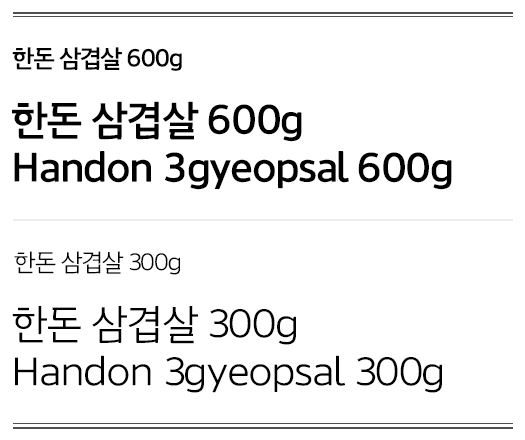
1.한돈 삼겹살체
한돈자조금관리위원회는 한돈데이(10.01)와 한글날을 기념하여 ‘한돈 삼겹살체’를 산돌커뮤니케이션과 공동 제작했다. 한돈의 친근하고 인간적인 이미지를 폰트에 녹여내기 위해 손글씨 형태로 기획되었다. 특히 자음 ‘ㄹ’은 마치 삼겹살을 겹겹이 올려놓은 것 같은 모양을 연상시켜 쓰는 즐거움도 제공한다.
한돈 삼겹살체는 Bold, Light 두 가지 웨이트로 구성되어 있고, 웨이트를 삼겹살 무게 600g과 300g으로 표현한 재치있는 작명도 눈길을 끈다. 한돈 삼겹살체는 한돈 홈페이지에서 회원가입 후 내려받아 사용할 수 있으며, 상업적인 행위는 금지되어 있다.
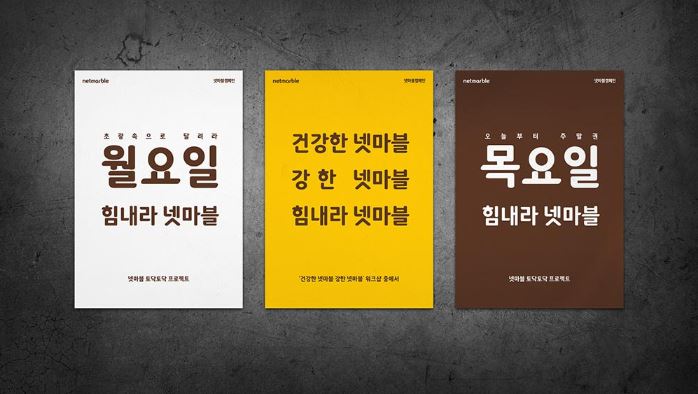
2. 넷마블체
넷마블은 기업의 정체성을 좀 더 친근하게 전달하고자 ‘넷마블체’를 제작했다. 이 폰트는 넷마블 마스코트 공룡 캐릭터인 ‘ㅋㅋ’의 실루엣을 형상화한 서체로 가독성을 고려해 만들어졌으며, 인쇄물이나 모니터에서 모두 잘 읽히는 것이 장점이다.
쭉 뻗은 직선이 매력적인 넷마블체는 Bold, Medium, Light 3종으로 구성돼 있다. 넷마블은 앞으로도 게임아카데미, 게임소통교육교재 등에 폰트를 적극적으로 활용할 예정이다.
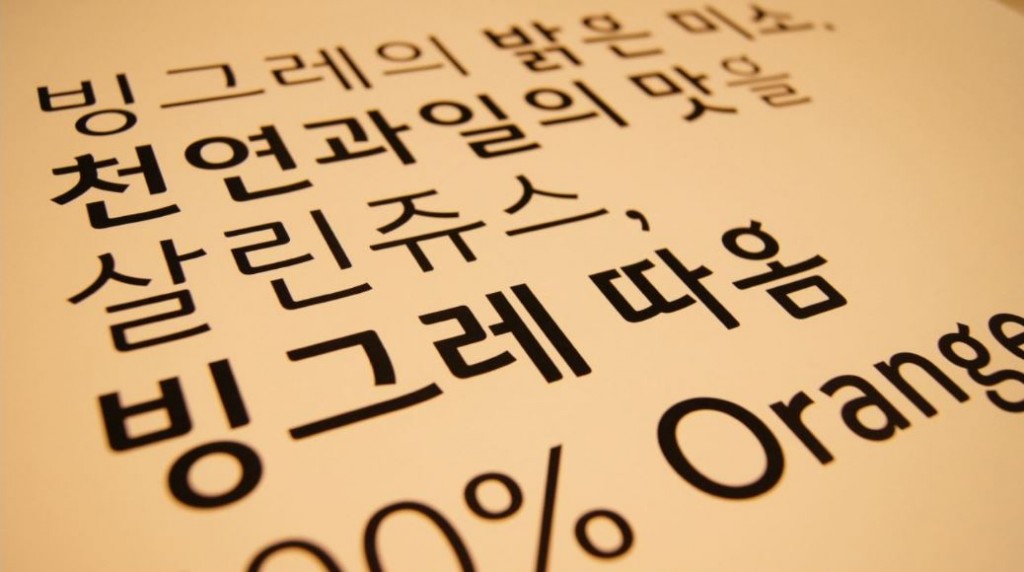
3. 빙그레 따옴체
바나나맛 우유 로고를 서체로 제작해 인기를 끌었던 빙그레는 한글 서체 시리즈 세 번째로 ‘빙그레 따옴체’를 출시했다. 과일쥬스 ’따옴’의 로고 디자인을 소재로 빙그레와 윤디자인그룹이 공동 제작하였다. 자음 이응에 쓰이는 나뭇가지 형상이 독특한 특징이다.
빙그레 따옴체는 한글날을 기념하여 훈민정음 서문의 옛한글 31자도 추가 됐으며, 세종대왕기념사업회와 한국글꼴개발연구원에 자문을 받았다.
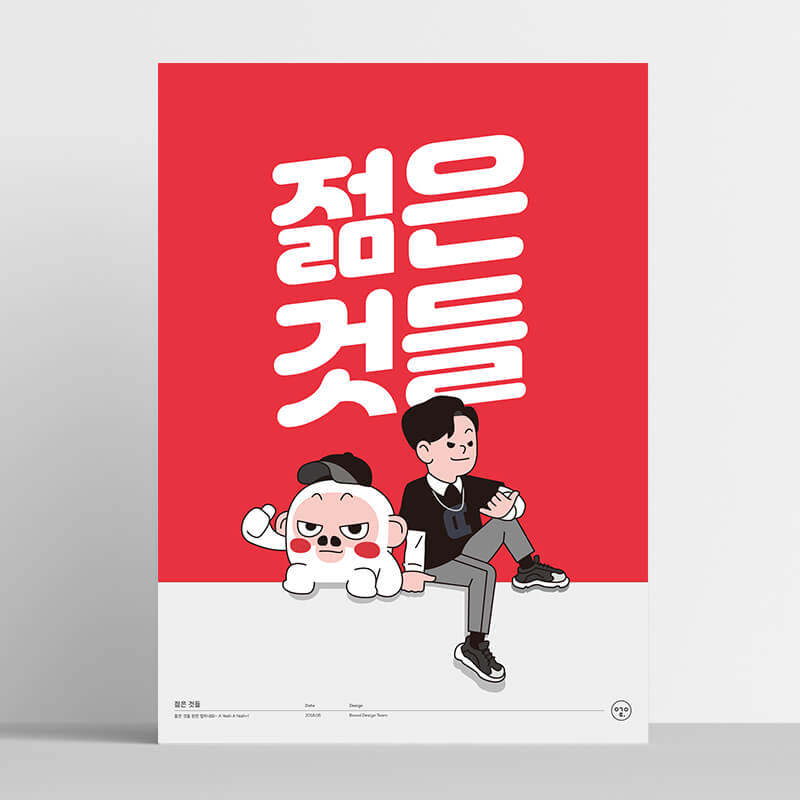
4. 여기어때 잘난체
위드이노베이션은 산돌커뮤니케이션과 함께 ‘잘난체’를 제작하여 배포했다. 잘난체는 여기어때 브랜드 이미지와 어울리는 젊고 발랄한 인상을 주는 서체다. 세로획의 윗부분은 둥글게, 아랫부분은 직선으로 처리하여 여기어때 로고의 이미지를 그대로 녹여냈다. 또한, 대표 캐릭터 ‘콩’이 딩벳폰트로 추가돼 다양하게 활용할 수 있다.
잘난체는 제목용으로 사용했을 때 가시성이 높으며, 상업적인 목적으로도 사용할 수 있다. 단, 배포된 파일을 그대로 사용해야 하며 글꼴 자체를 유료로 판매하거나 임의 수정하는 것은 금지되어 있다.
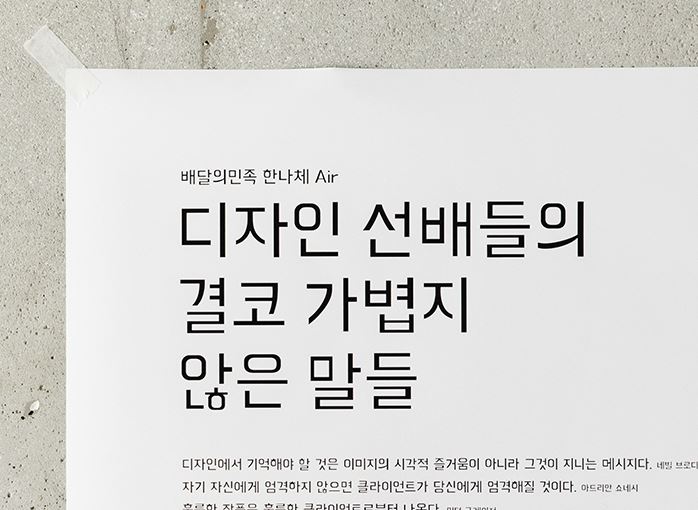
5 .배달의 민족 한나체 Air
우아한형제들은 아름다운 한글을 누구나 제약 없이 쓸 수 있도록 폰트를 만들어 배포하고 있다. 가장 큰 인기를 끌었던 ‘한나는열한살’을 본문용으로 사용할 수 있도록 ‘한나체 Air’가 출시되었다. 얇은 웨이트의 한나체 Air는 작게 쓸수록 가독성을 높아지는 점이 특징이다.
기존의 배달의민족 서체들은 투박하고 강한 개성을 지녔다면, 한나체 Air는 좀 더 가볍고 감성적인 느낌을 주며, 곧 한나체 시리즈인 ‘한나체 Pro’도 출시될 예정이다.